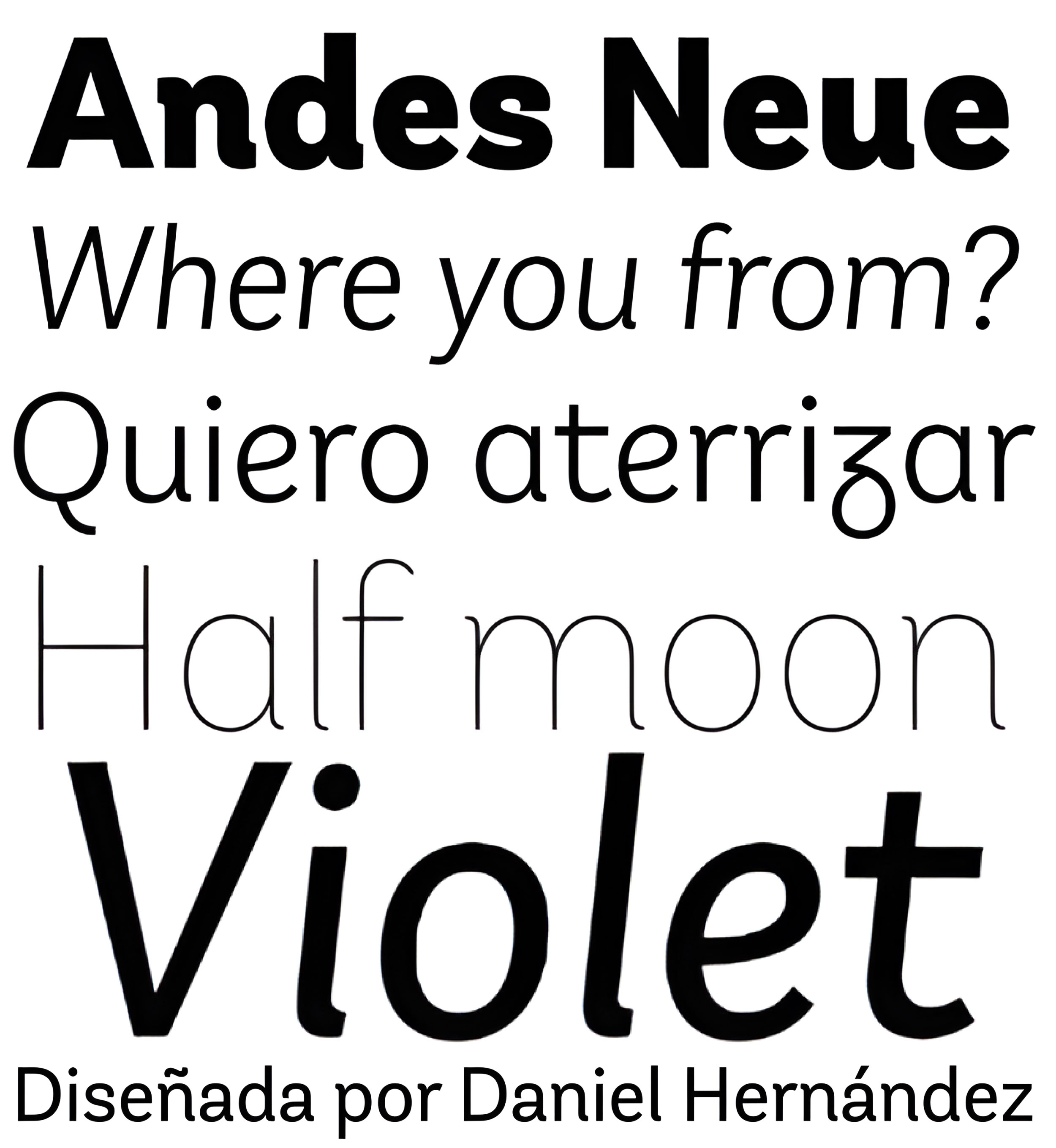
| Descripción | A diferencia de su predecesor, Andes Neue contiene un juego de caracteres más amplio, de 759 glifos, compatible con 219 lenguas de base latina de 212 países. La fuente se presenta en 4 variantes que ofrecen una amplia gama estilística. Andes Neue es la más similar al diseño original de Andes. El juego de caracteres Alt1 guarda cierta similitud con el de la antigua Andes (aunque más limpio); Alt2 utiliza los alternativos de la fuente como glifos por defecto; y Alt3 es una mezcla de las otras tres variantes que ofrece un conjunto equilibrado de caracteres. Andes Neue también incluye nuevos acentos y glifos para una mayor compatibilidad lingüística, y un juego de versalitas (en cada variante). Todas estas características confieren a la fuente una fuerte personalidad que ayuda a que el texto resulte más atractivo. Los variados pesos de Andes Neue funcionan bien tanto con secciones de texto cortas como de longitud media, ofreciendo una amplia gama de opciones para cualquier proyecto de diseño. |